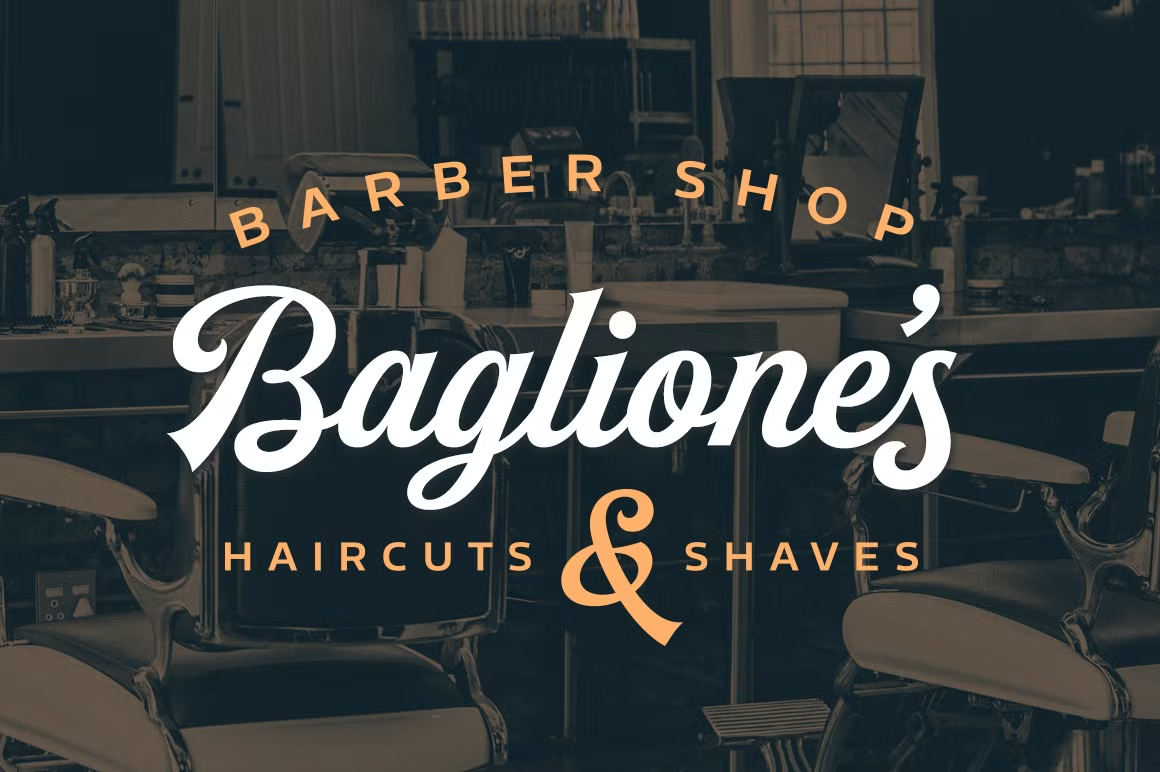
Buinton Font
Description de Buinton Font
Buinton est une police d’écriture classique qui incarne la noblesse et l’attrait rétro. Fabriqué avec le plus grand soin, il comprend des empattements au début des traits, des traits en majuscules et un design formel. Lié à divers caractères alternatifs, swashes et ligatures, Buinton offre aux designers de nombreuses opportunités de créativité.
La collection unique de personnages alternatifs offerte à Buinton est l’une de ses meilleures caractéristiques. Que vous souhaitiez une esthétique de logo vintage ou une ambiance sportive, Buinton propose les personnages alternatifs qui vous aident à obtenir ce que vous voulez. De plus, la police se compose d’une gamme de queues de formes et de largeurs assorties, ce qui lui confère un aspect vintage et permet d’être adaptée à des demandes de conception spécifiques.
La police de caractères script est très polyvalente et convient donc à de nombreuses applications. De la conception de logos sophistiqués à la production de lettrages intrigants, de la création de graphiques de t-shirts attrayants à la présentation d’illustrations éditoriales stimulantes, Buinton est clairement un outil irremplaçable dans l’arsenal du designer.
Buinton est une belle police au son vintage qui donnera à tout projet une impression de classe. Avec son design formel et ses détails complexes, il est parfait pour transmettre élégance et sophistication. L’abondance de personnages et de swashes alternatifs permet des expériences créatives infinies.
En résumé, Buinton est une police d’écriture flexible et universelle qui transcende les frontières et stimule l’imagination. Qu’il soit utilisé pour le branding, la typographie ou l’illustration, son esthétique noble et son charme vintage en font une option attrayante pour les designers qui souhaitent créer un fort impact avec leur travail.